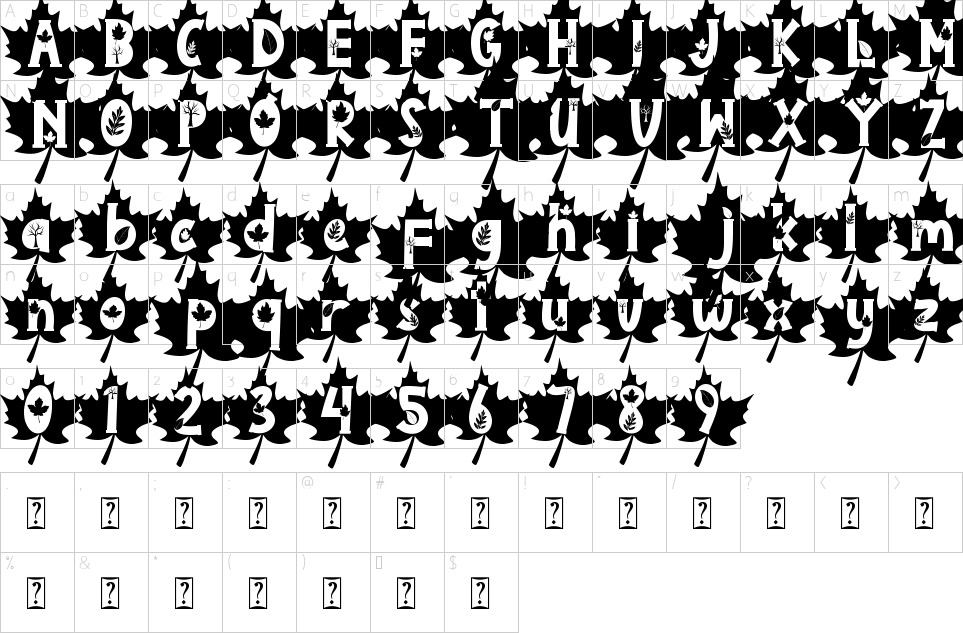
Grateful Autumn Font – Fonte Grátis
Grateful Autumn Font
Descubra a beleza do Grateful Autumn Font para Windows e Mac. Desenvolvida pela Selvia Design, esta elegante fonte oferece uma textura sofisticada que se adapta perfeitamente aos momentos de gratidão e reflexão. Com seus 162 downloads, o Grateful Autumn é um recurso gratuito que você certamente vai querer incorporar em seu próximo projeto visual. Seja para mensagens pessoais ou design gráfico, essa fonte adorna com elegância e estilo qualquer texto ao qual for aplicada. Quebre o gelo das suas mensagens com a beleza deste projeto de fonte única. Descubra agora Grateful Autumn Font e transforme seu design em um elemento de arte que fala sem palavras.